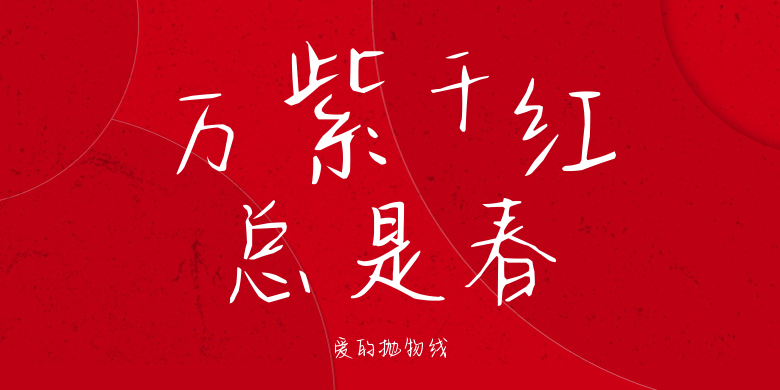
爱的抛物线
爱的抛物线,这款字体结构工整、笔画清晰,兼顾美观与易读性,适用于标题、正文、海报、包装、LOGO 等多种场景。字形优雅稳定,风格百搭耐看,适配日常排版与创意设计,让文字呈现更舒适、更具质感。爱的抛物线一笔一画,皆是细节,以均衡的比例、流畅的线条打造舒适视觉体验,字形端正大气,风格简约现代。无论是商业设计、品牌宣传还是日常排版,都能轻松驾驭,让文字更有格调与力量。爱的抛物线字体下载。